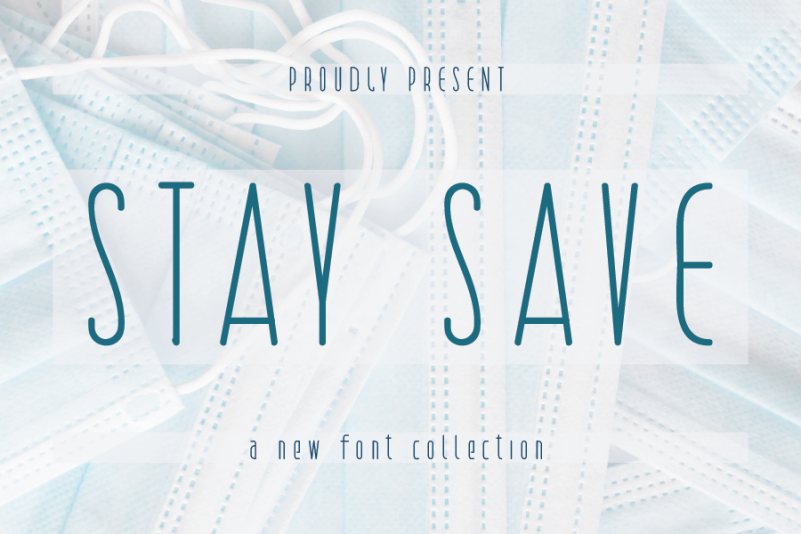
STAY SAVE Font – Download Grátis
Esta é uma fonte script bem equilibrada e refinada que transmite sofisticação e elegância. Com alternativas estilizadas e ligaturas sofisticadas, ela se destaca como a escolha ideal para qualquer projeto visual. A designer handwrittenwanda trouxe uma sensação leve de escrever livremente à mão, ao mesmo tempo em que mantém um equilíbrio perfeito entre o formal e o elegante. É perfeitamente adaptável às necessidades de design de qualquer empresa ou projeto, seja para criações de identidade corporativa, materiais de marketing ou até mesmo para artigos de blog. A fonte ‘STAY SAVE Font’ tem um tom amigável que encoraja os designers a explorarem e a criarem seus próprios designs com esta graciosamente fluida ferramenta.
Designer: handwrittenwanda